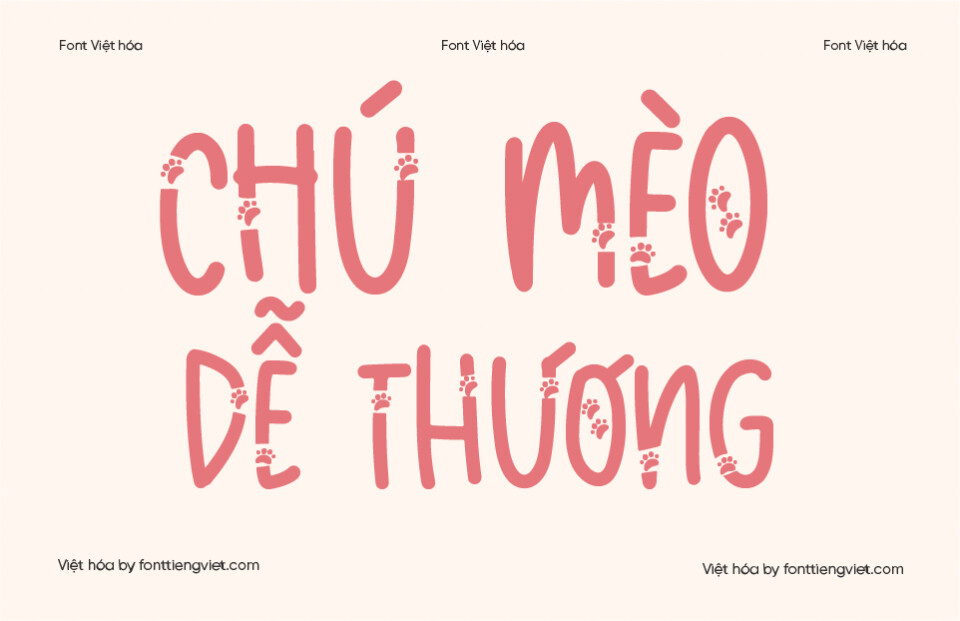
Font 1FTV VIP Meow Paw Việt Hóa – Font Dễ Thương Chủ Đề Mèo Cho Thiết Kế Poster
Trong thế giới sáng tạo, việc lựa chọn một Font Chữ phù hợp đóng vai trò quan trọng trong việc truyền tải cảm xúc của tác phẩm. Đặc biệt, đối với các bạn học sinh hay thầy cô giáo, Font 1FTV VIP Meow Paw Việt Hóa – Font Dễ Thương Chủ Đề Mèo Cho Thiết Kế Poster chính là “chân ái” mang lại sự đáng yêu và gần gũi. Bộ font này không chỉ nổi bật bởi nét chữ tròn trịa mà còn gây ấn tượng mạnh mẽ nhờ những hình ảnh dấu chân mèo ngộ nghĩnh, giúp sản phẩm thiết kế trở nên sinh động và thu hút hơn bao giờ hết.
Khám phá sức hút của Font 1FTV VIP Meow Paw Việt Hóa – Font Dễ Thương Chủ Đề Mèo Cho Thiết Kế Poster
Lý do khiến bộ font này được yêu thích nằm ở sự kết hợp hoàn hảo giữa tính thẩm mỹ và tính ứng dụng cao. Đây là lựa chọn hàng đầu cho các dự án hướng đến trẻ em hoặc những người yêu thú cưng.
Đặc điểm nổi bật của font mèo dễ thương
Bộ font này đã được Việt hóa chỉn chu, giúp người dùng dễ dàng gõ tiếng Việt có dấu mà không lo lỗi font. Từng nét vẽ được mô phỏng theo hình dáng bàn chân mèo mềm mại, tạo cảm giác thân thiện. Điều này giúp các ấn phẩm tuyên truyền tại nhà trường hoặc poster sự kiện câu lạc bộ trở nên nổi bật và mang đậm dấu ấn cá nhân.
Ứng dụng thực tế trong giáo dục và thiết kế
Bạn có thể sử dụng font này để thiết kế thiệp mời, trang trí báo tường hoặc làm nổi bật các tiêu đề trên poster. Sự ngộ nghĩnh của nó giúp nội dung trở nên dễ tiếp nhận, khơi gợi niềm vui và sự hứng khởi cho người xem ngay từ cái nhìn đầu tiên.
Kết luận về bộ font mèo độc đáo
Việc sử dụng Font 1FTV VIP Meow Paw Việt Hóa – Font Dễ Thương Chủ Đề Mèo Cho Thiết Kế Poster sẽ giúp các bạn tự tin hơn trong việc sáng tạo những ấn phẩm mang phong cách trẻ trung và hiện đại. Hãy nhanh tay trải nghiệm Font Miễn Phí, Font Việt Hóa, Font 1FTV VIP Meow Paw Việt Hóa – Font Dễ Thương Chủ Đề Mèo Cho Thiết Kế Poster để biến những ý tưởng thiết kế của bạn thành hiện thực một cách hoàn mỹ nhất.